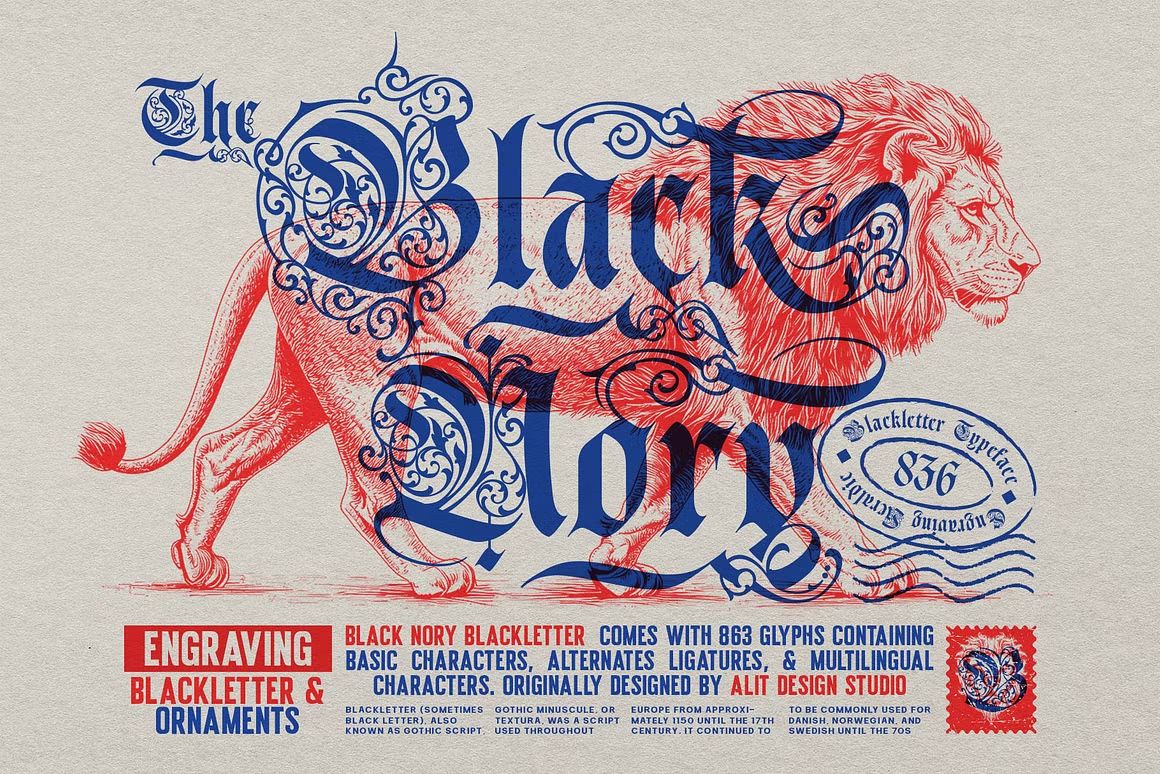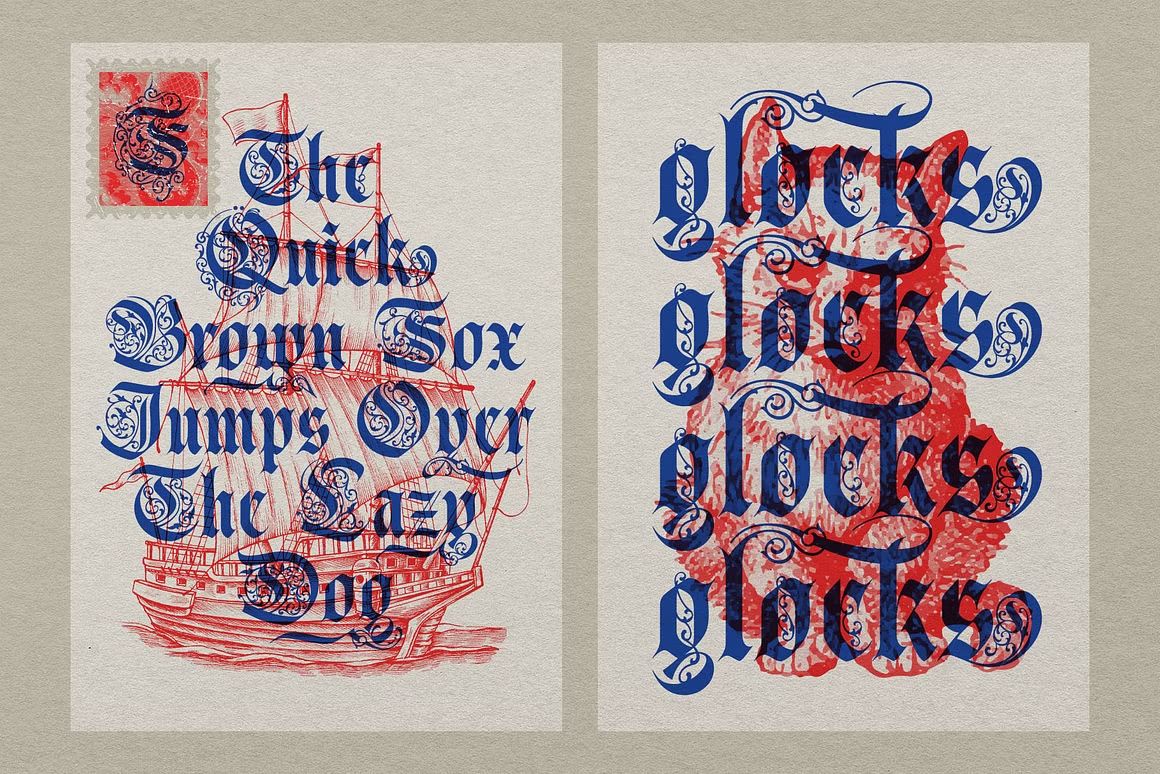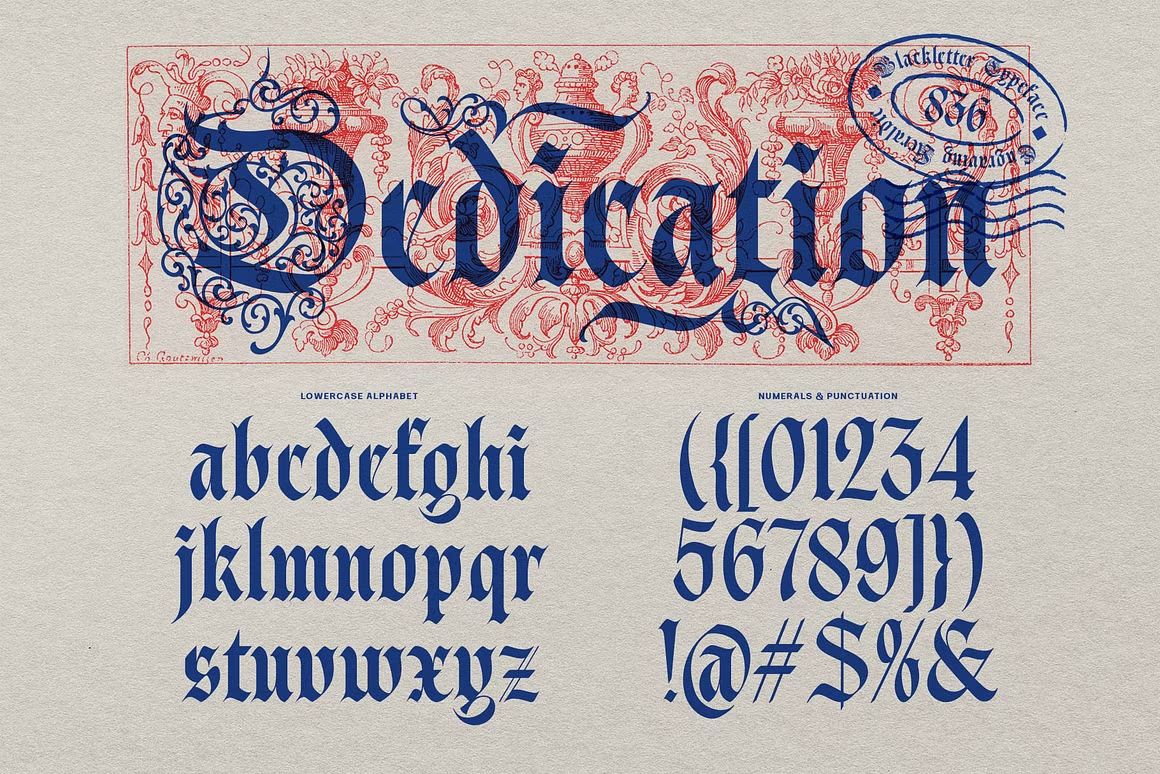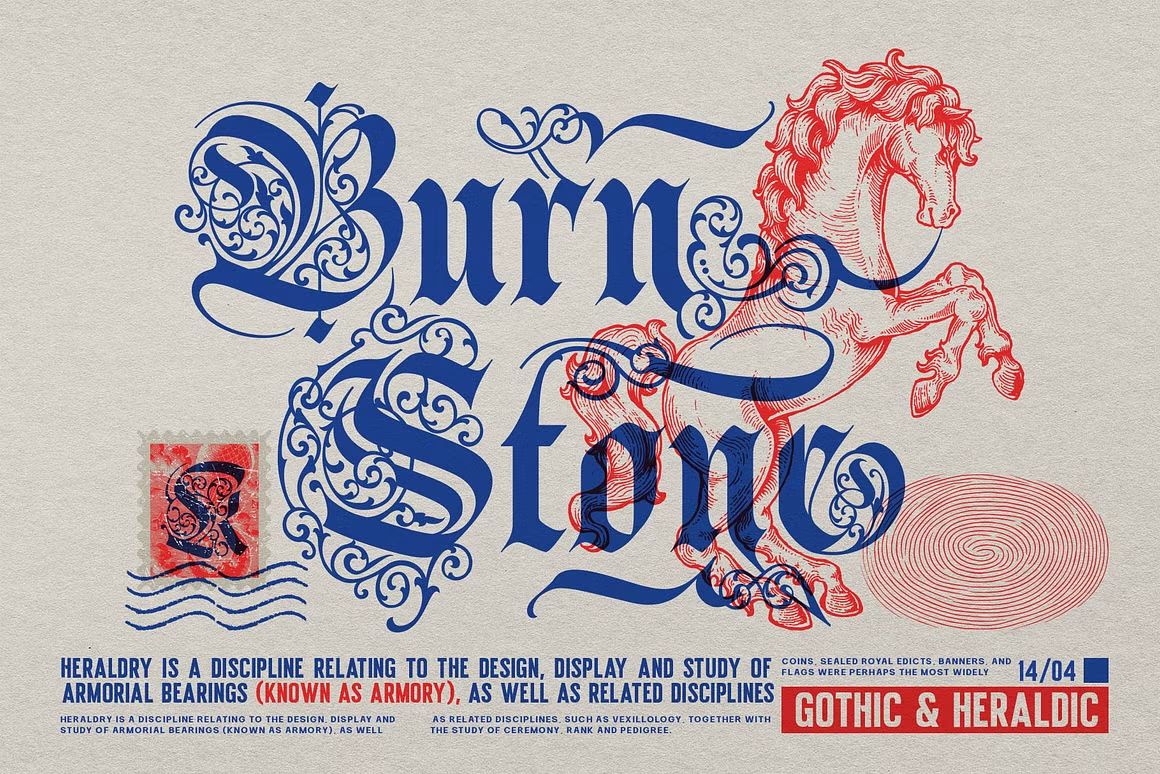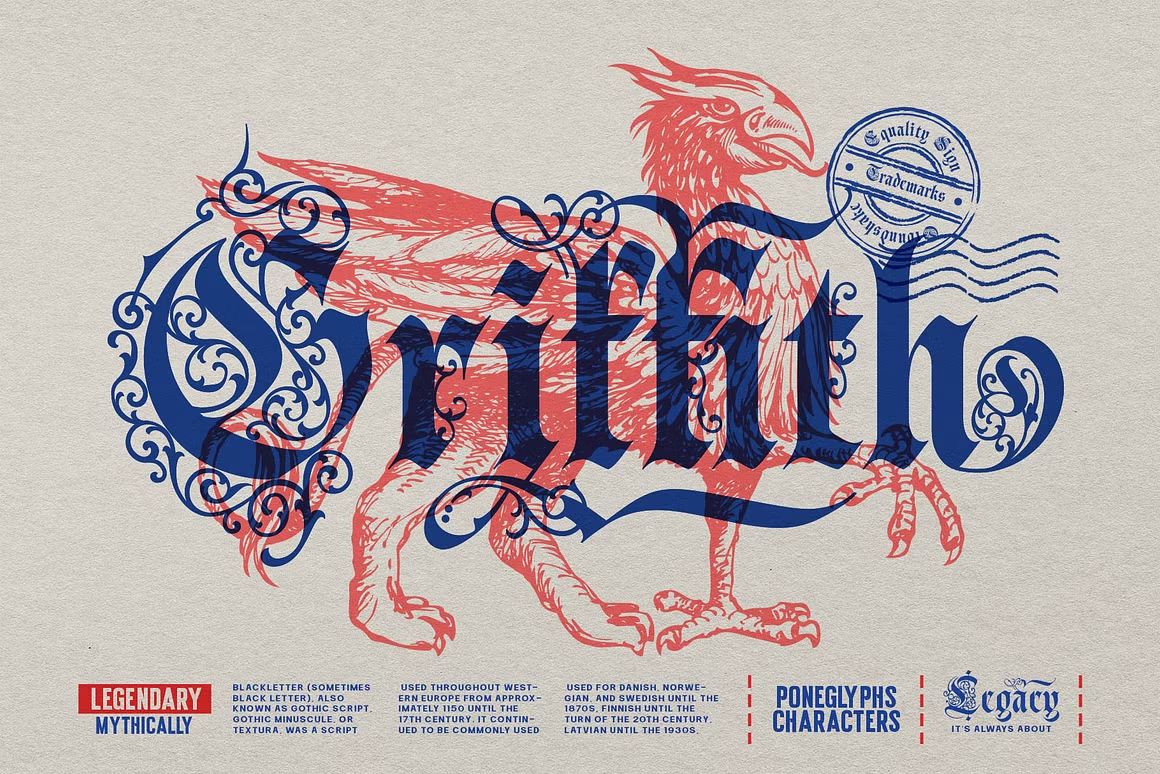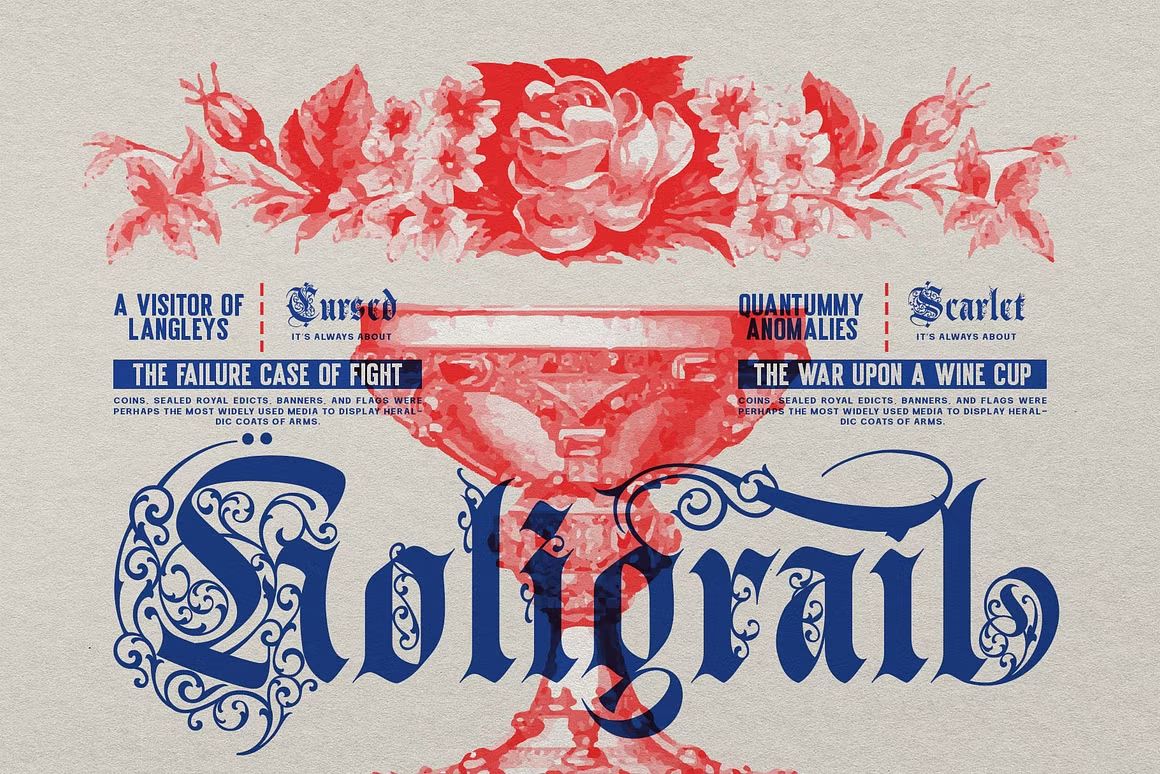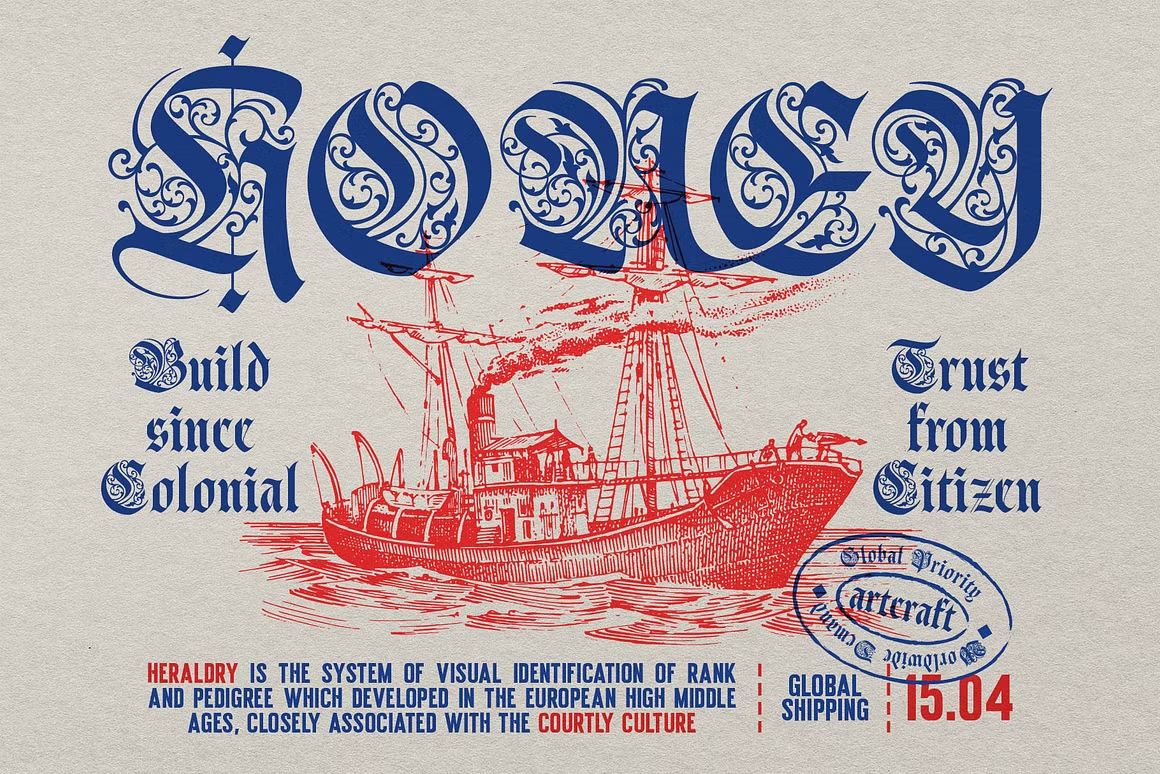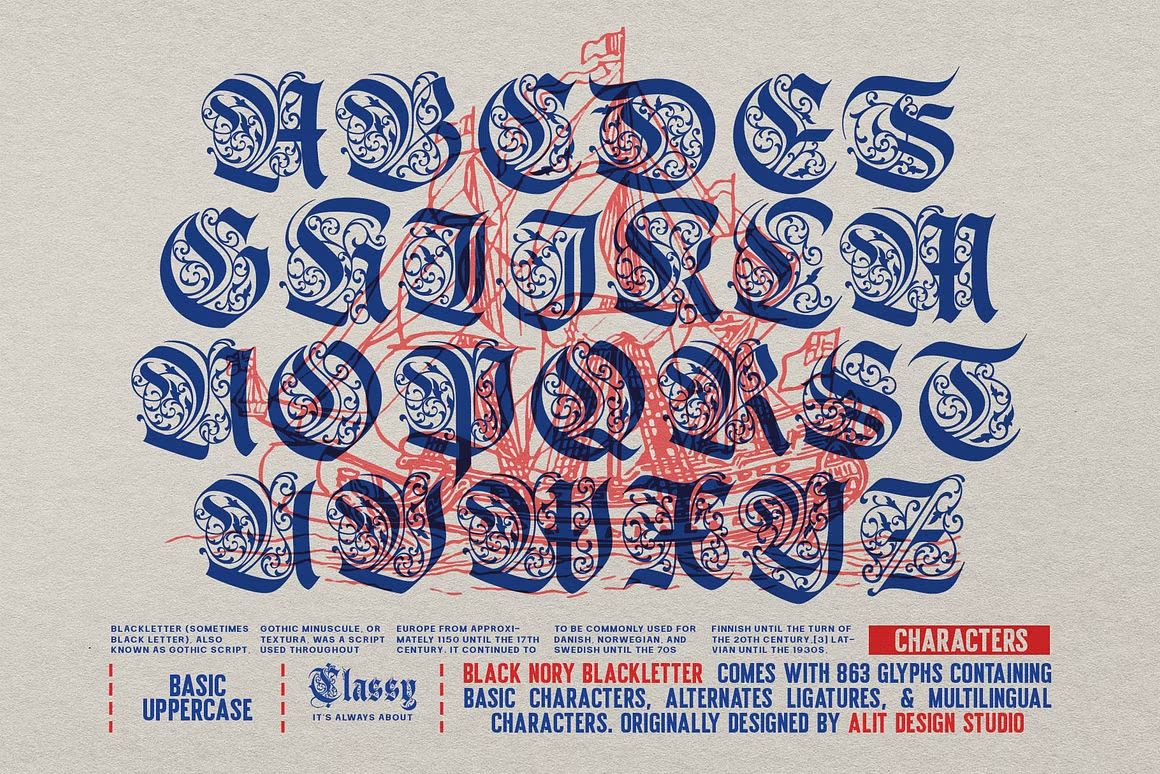
Black Nory – Blackletter Font
Black Nory adalah font blackletter bergaya gothic modern yang menghadirkan tampilan kuat, berani, dan penuh karakter. Dengan bentuk huruf tajam dan ornamen klasik, font ini ideal untuk desain bertema musik, tattoo, streetwear, poster vintage, atau branding yang mengutamakan kesan maskulin dan dramatis. Black Nory memberikan nuansa klasik yang tetap relevan di era modern.
• Gaya blackletter klasik dengan sentuhan modern
• Cocok untuk desain musik, fashion, dan poster edgy
• Termasuk huruf kapital, kecil, angka, dan simbol